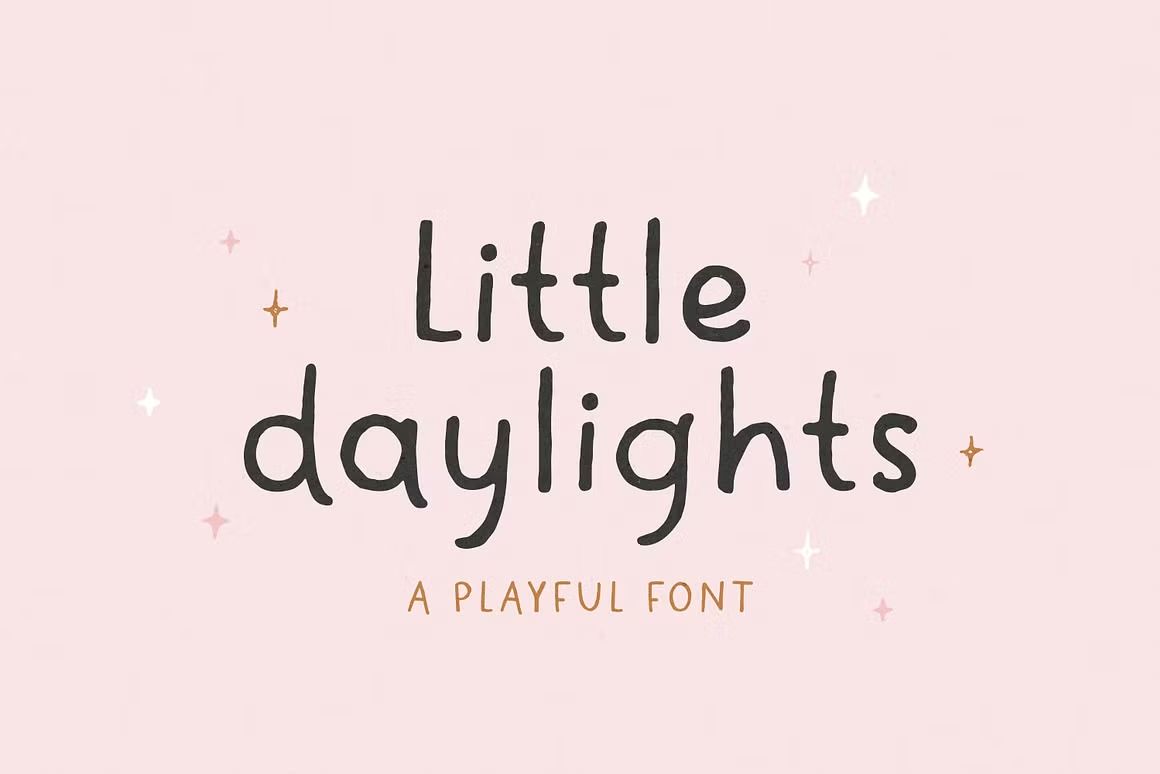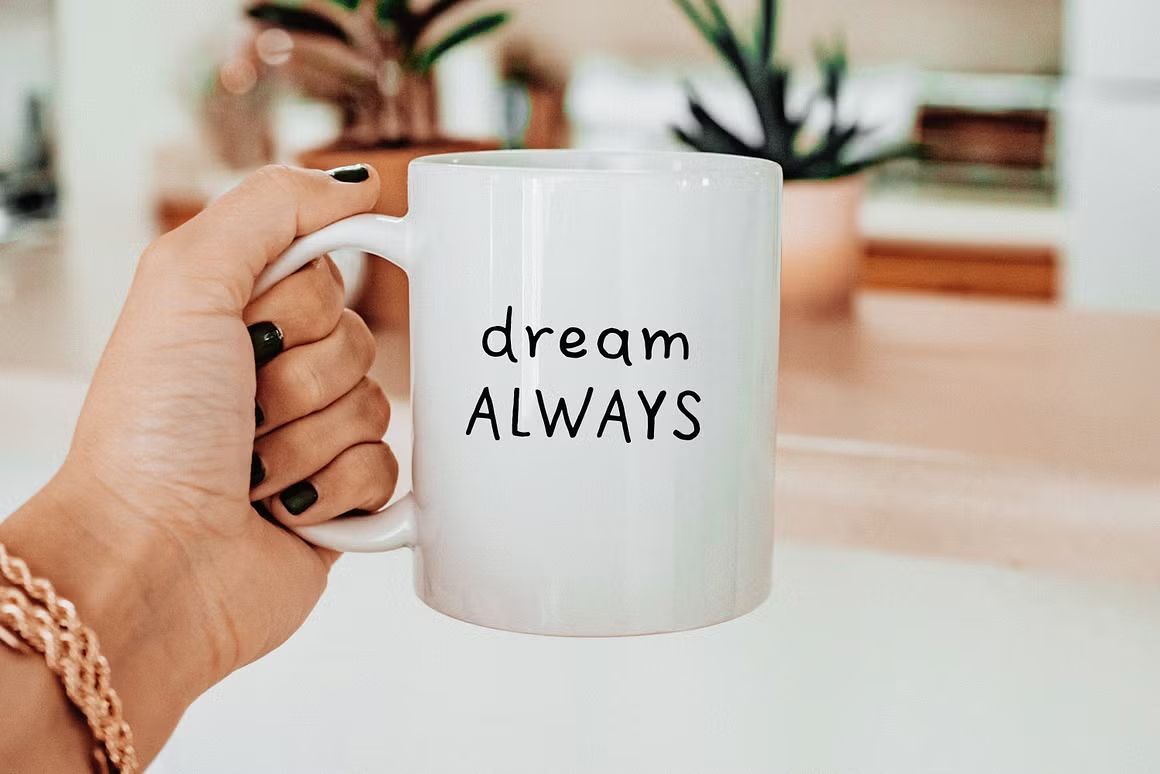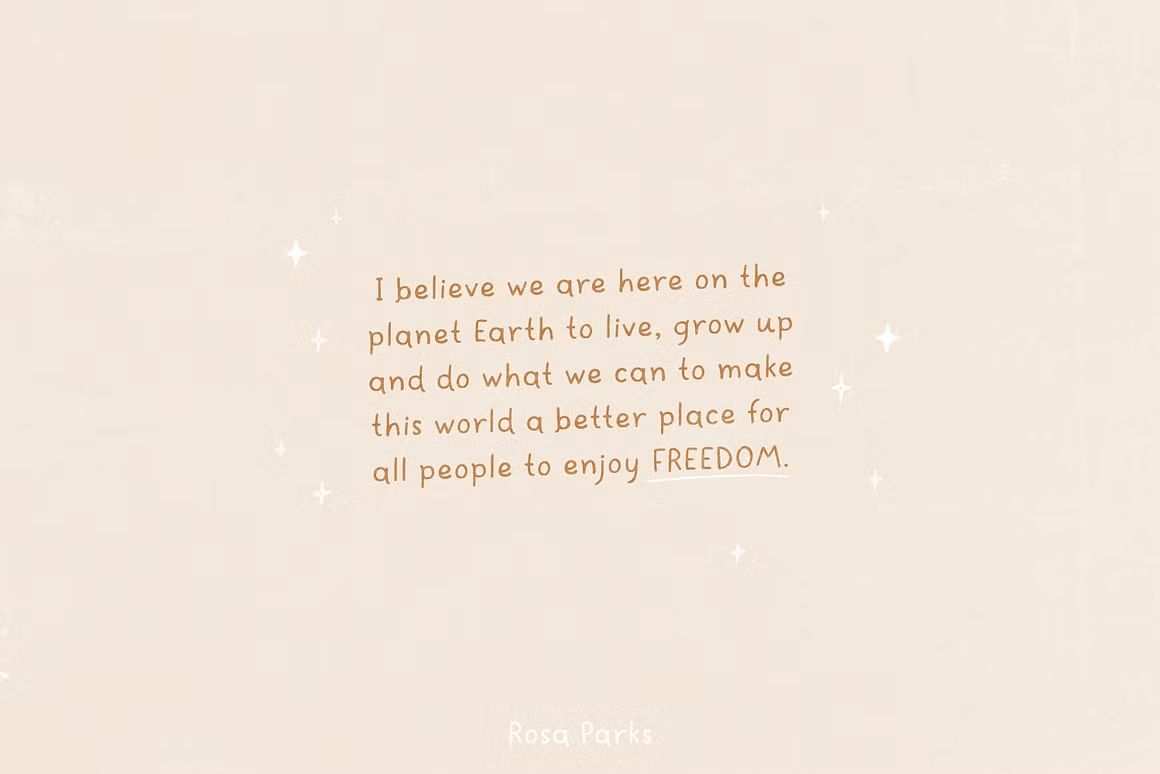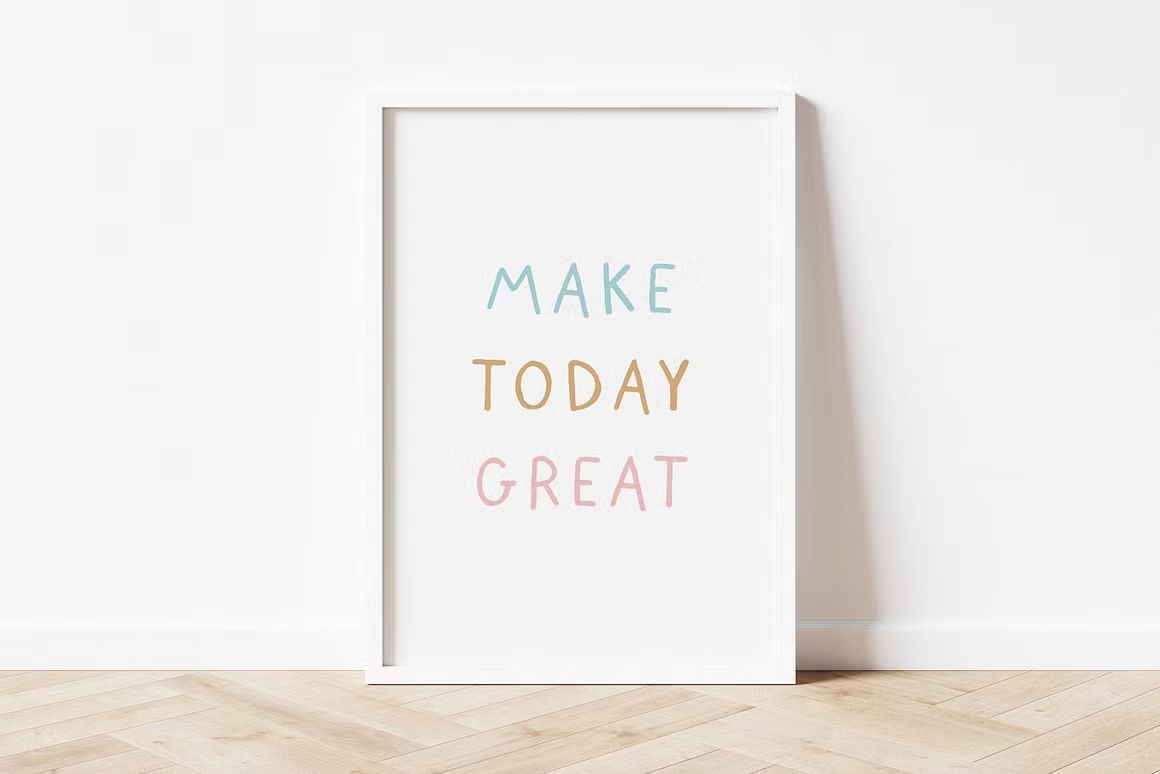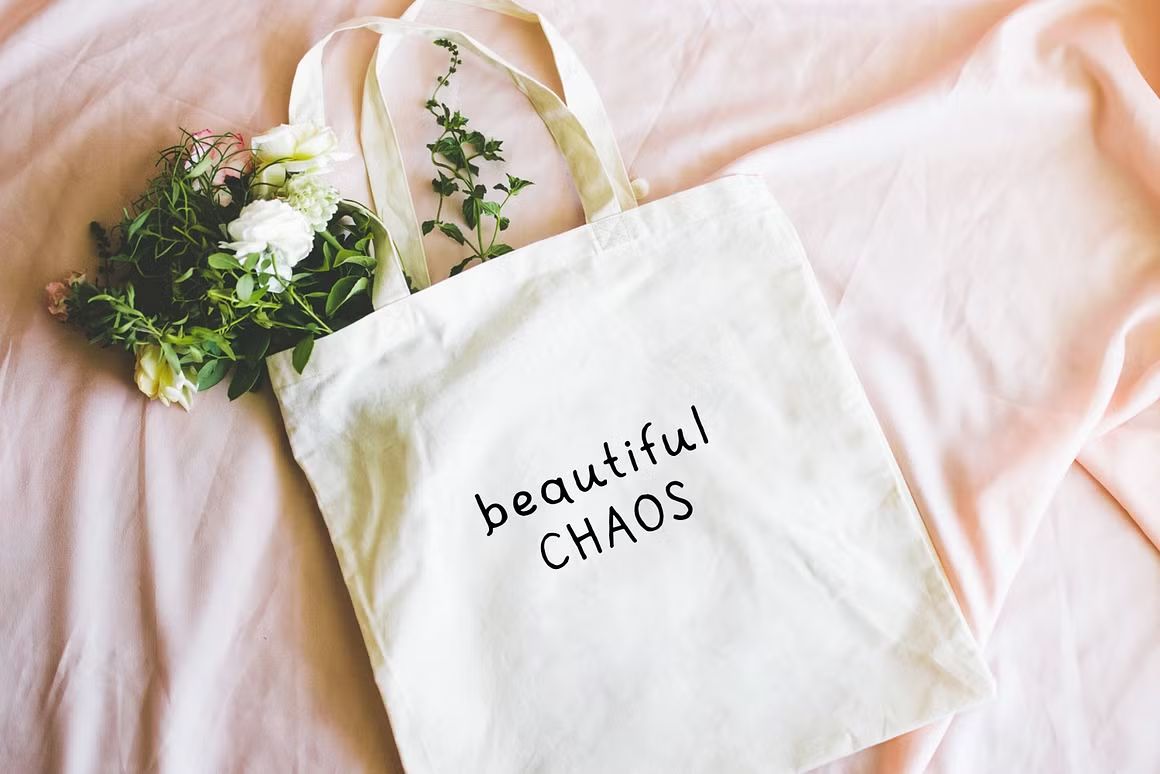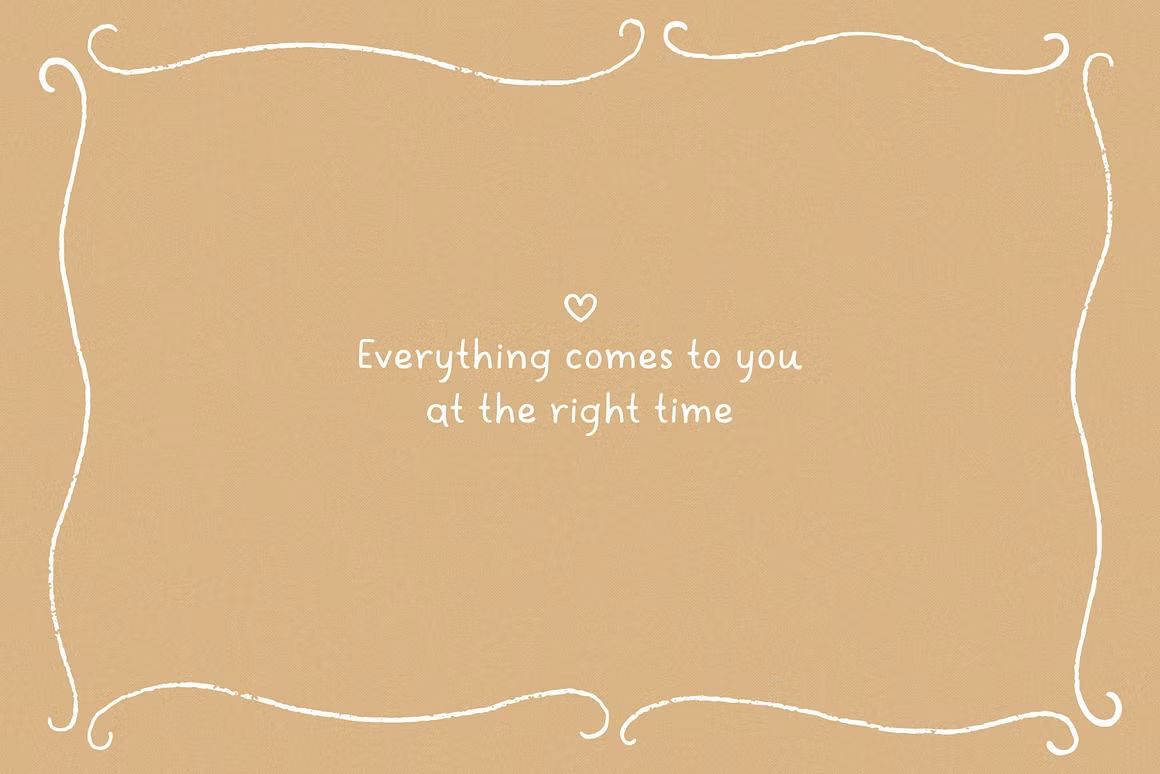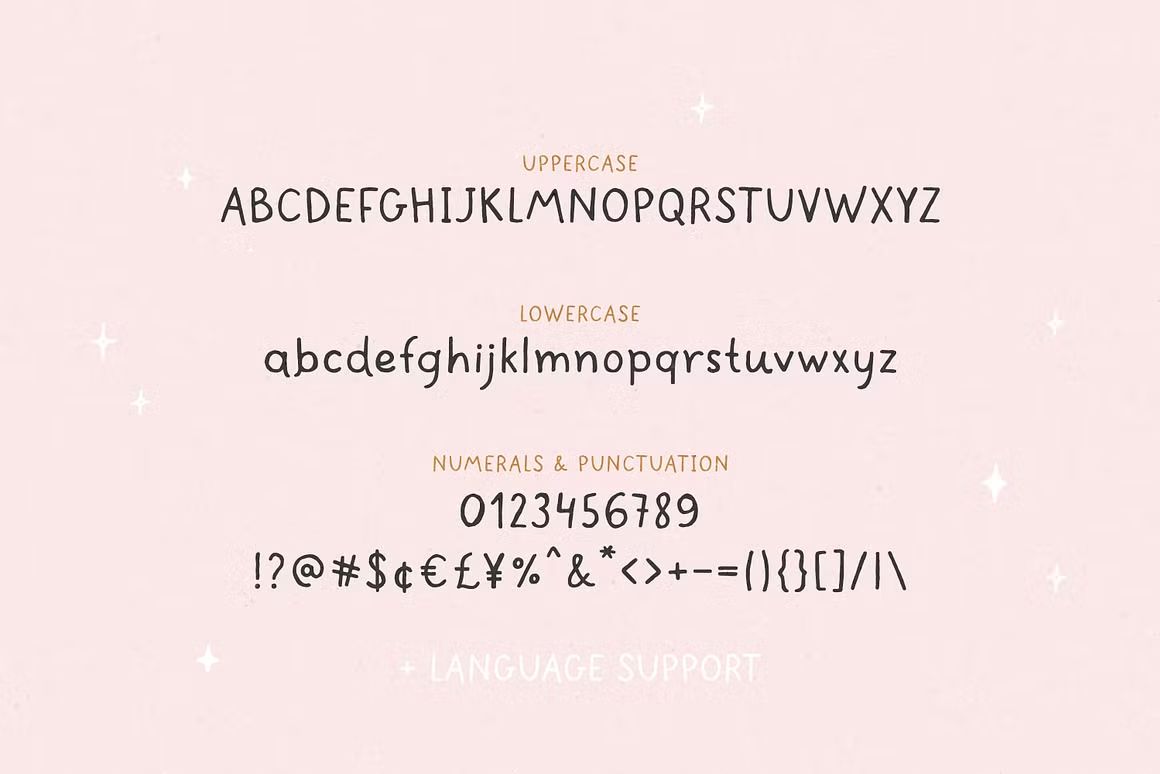
Little Daylights – Handwritten Font
Little Daylights adalah font handwritten yang lucu dan ringan, cocok untuk desain anak-anak dan konten personal. Format OTF/TTF/WOFF, siap digunakan.
Little Daylights adalah font handwritten dengan gaya lucu, ringan, dan natural. Didesain menyerupai tulisan tangan santai, font ini sangat cocok untuk desain bertema anak-anak, jurnal pribadi, undangan informal, kutipan manis, dan konten media sosial yang bersahabat. Tampilan yang playful namun tetap rapi menjadikan Little Daylights ideal untuk proyek kreatif yang ingin tampil hangat dan personal.
• Handwritten font dengan gaya ringan dan ramah
• Cocok untuk desain anak, journaling, dan media sosial
• Termasuk huruf besar, kecil, angka, dan simbol